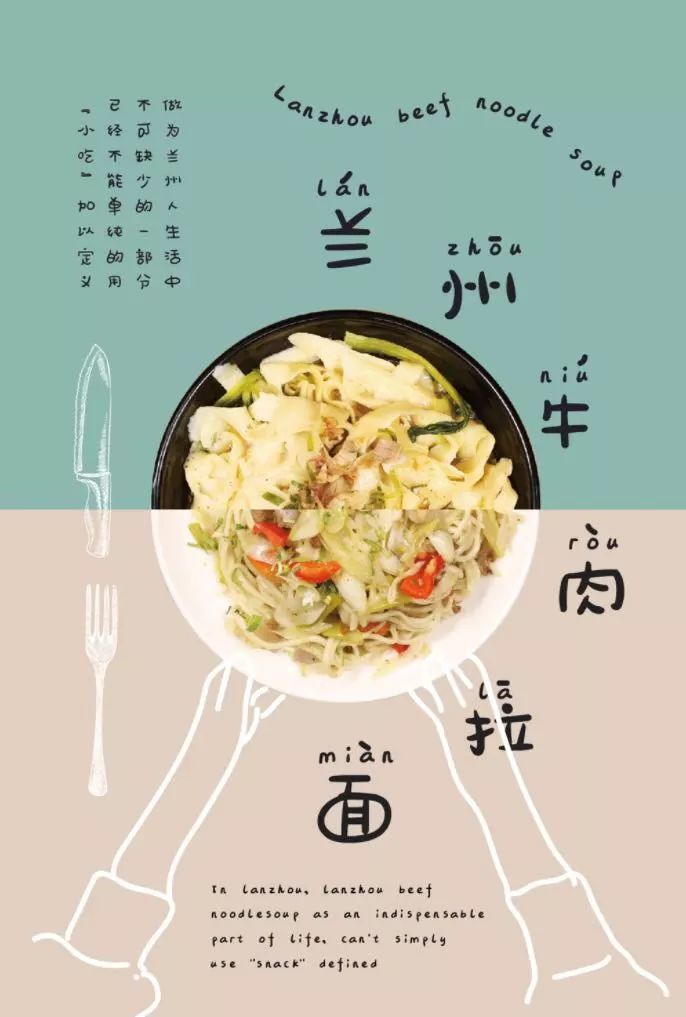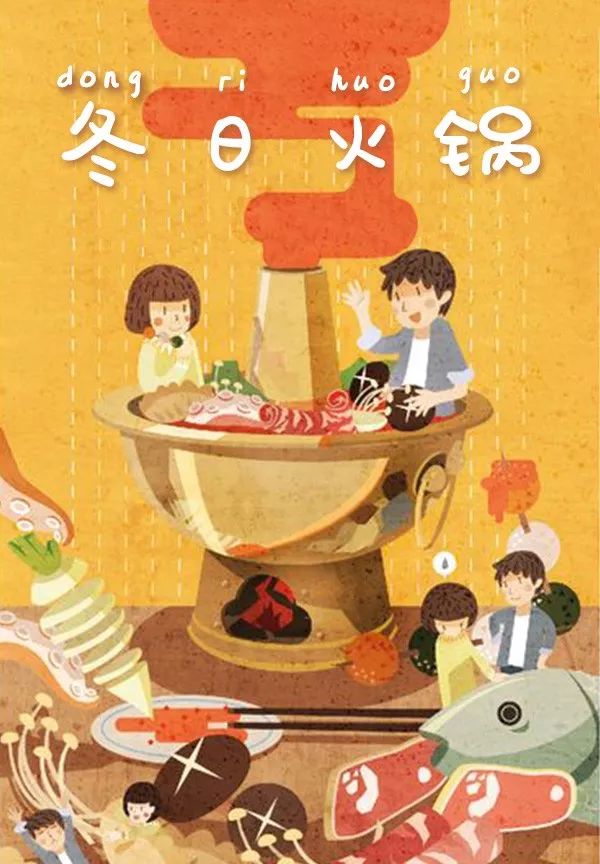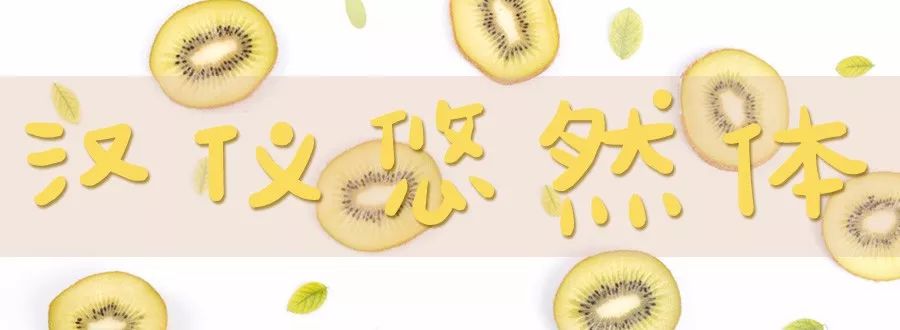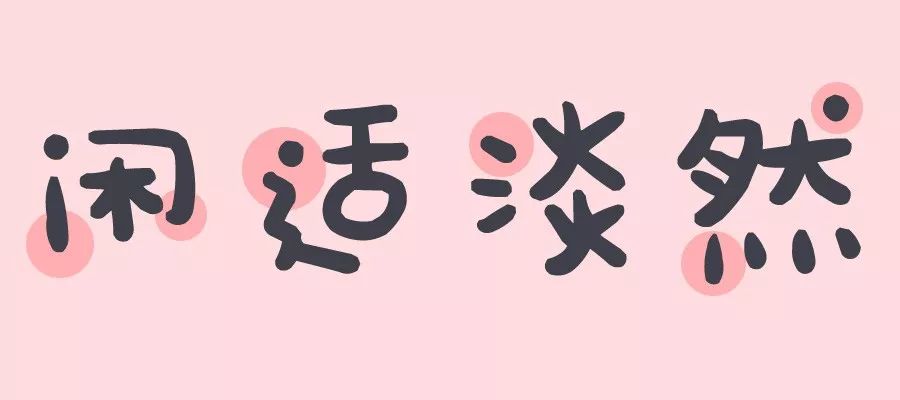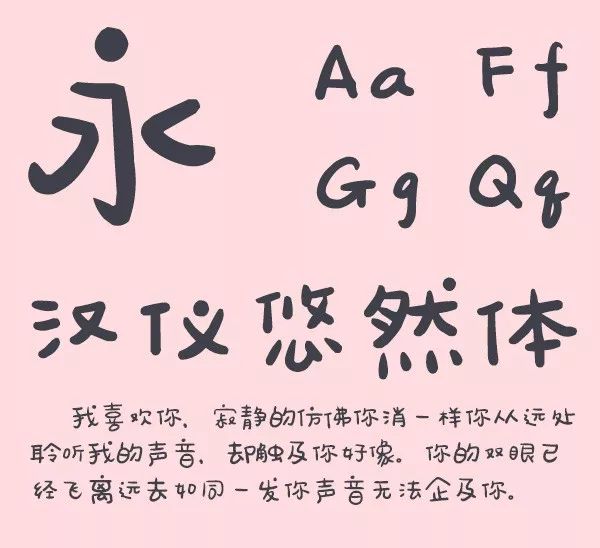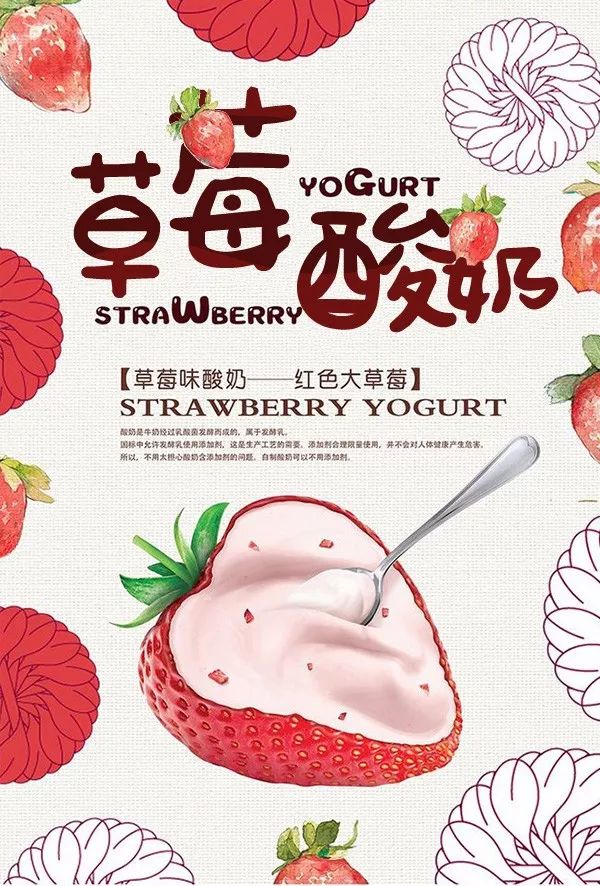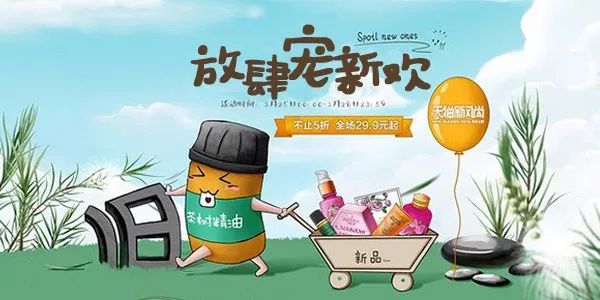
汉仪悠然体,非常适合美食、餐饮的字体分享
这么有食欲且温馨的画面用什么字点缀才
最合适呢?
这样?
哦,NO‼
这样?
靠,what are you 弄啥嘞
还是这样?
诶呦不错哦!
是不是觉得顿时食欲倍增
今天给大家带来的这款
倍儿有食欲感的字体就是
汉仪悠然体
纯手写的悠然体如字体名称一样
在注重随性、闲适的同时
不失俏皮的一面
字体的“口”部及点
均使用圈和圆代替
为字体增添了更多的可爱及趣味元素
宽松的字间距平稳的视觉重心
活跃的字面让文字趣味倍增
最后的案例展示也不错哦